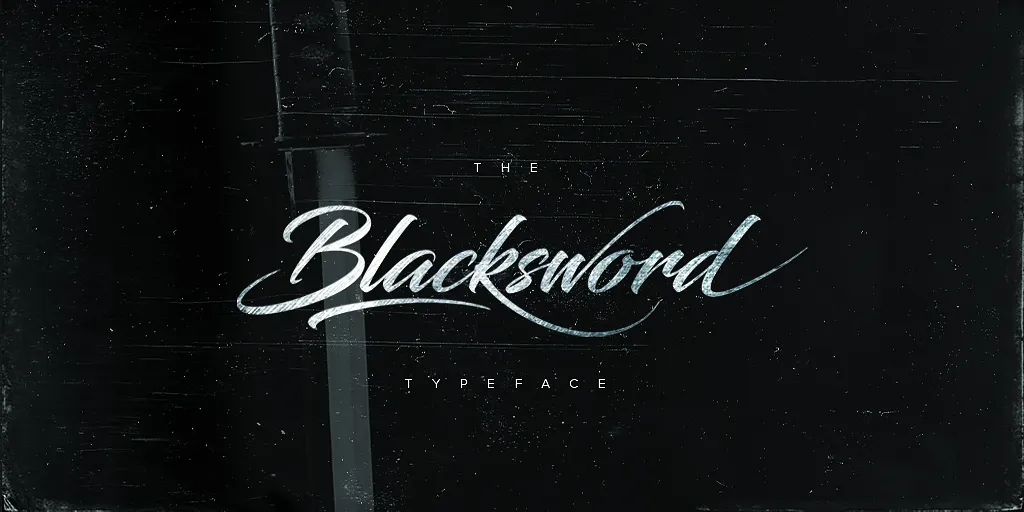
Esta fonte ‘Blacksword Font’ é perfeita para quem busca algo único e distintivo no seu próximo projeto visual. Desenhada pelo talentoso designer Hamilton, esta fonte Brush está disponível gratuitamente para uso pessoal, tornando-a uma opção ideal para designers, ilustradores ou qualquer profissional que esteja buscando um toque autêntico em seus projetos. Para qualquer aplicação comercial, contate-nos e exploraremos juntos as possibilidades de usar esta fantástica fonte na sua próxima campanha publicitária ou projeto web. Com seu design robusto e elegante, Blacksword Font será uma escolha inteligente para tornar seus projetos mais memoráveis e criativos.